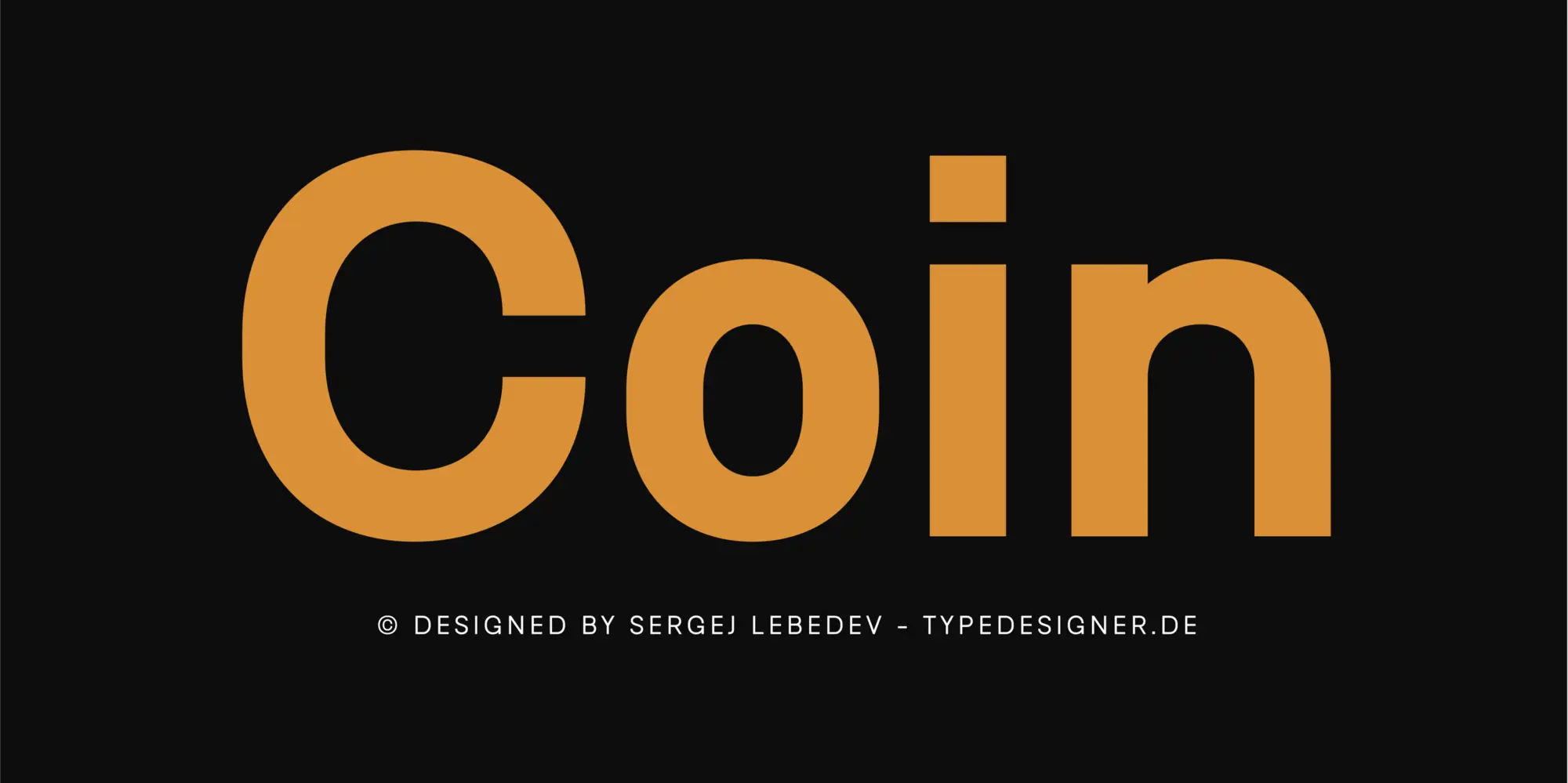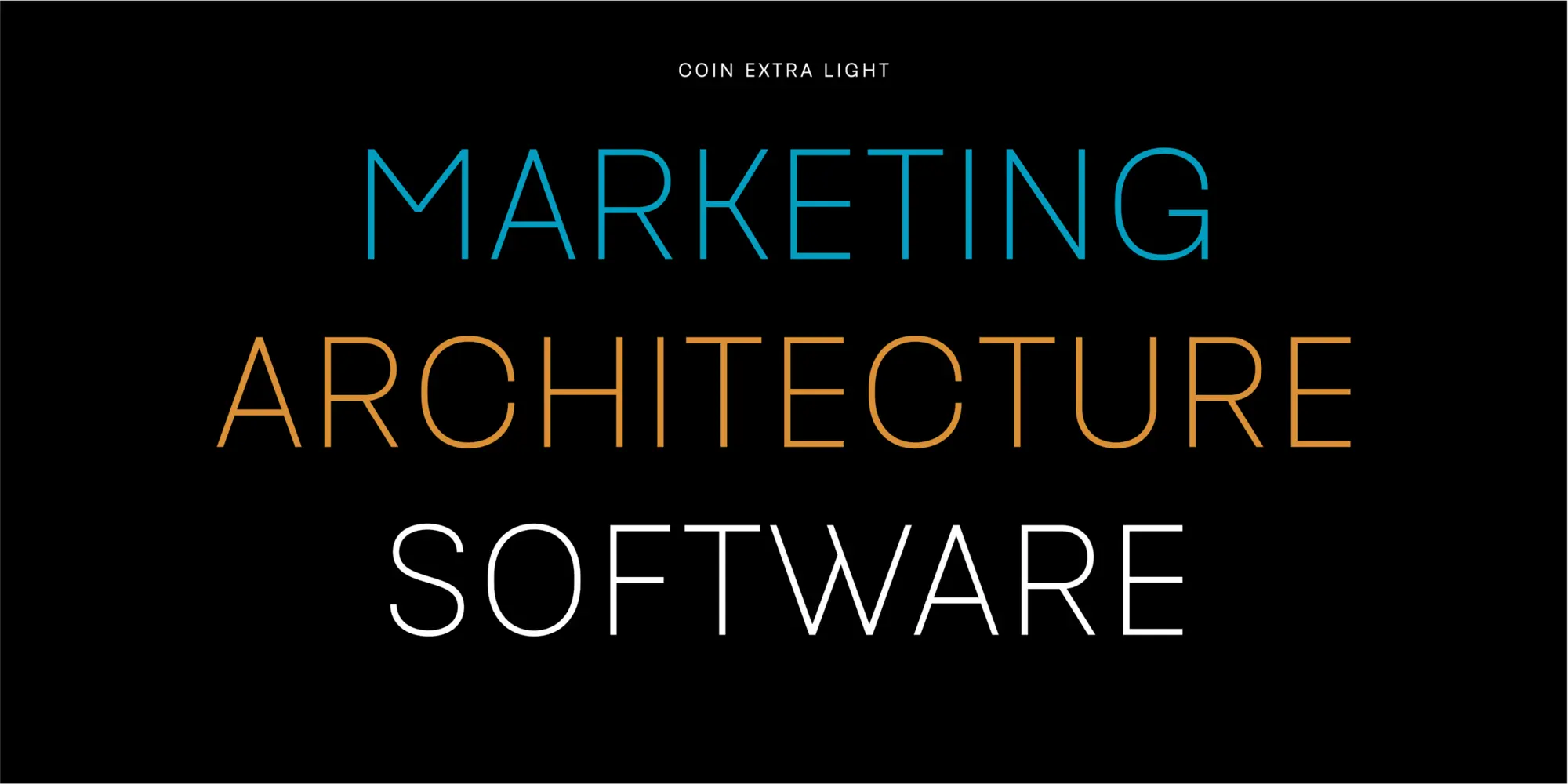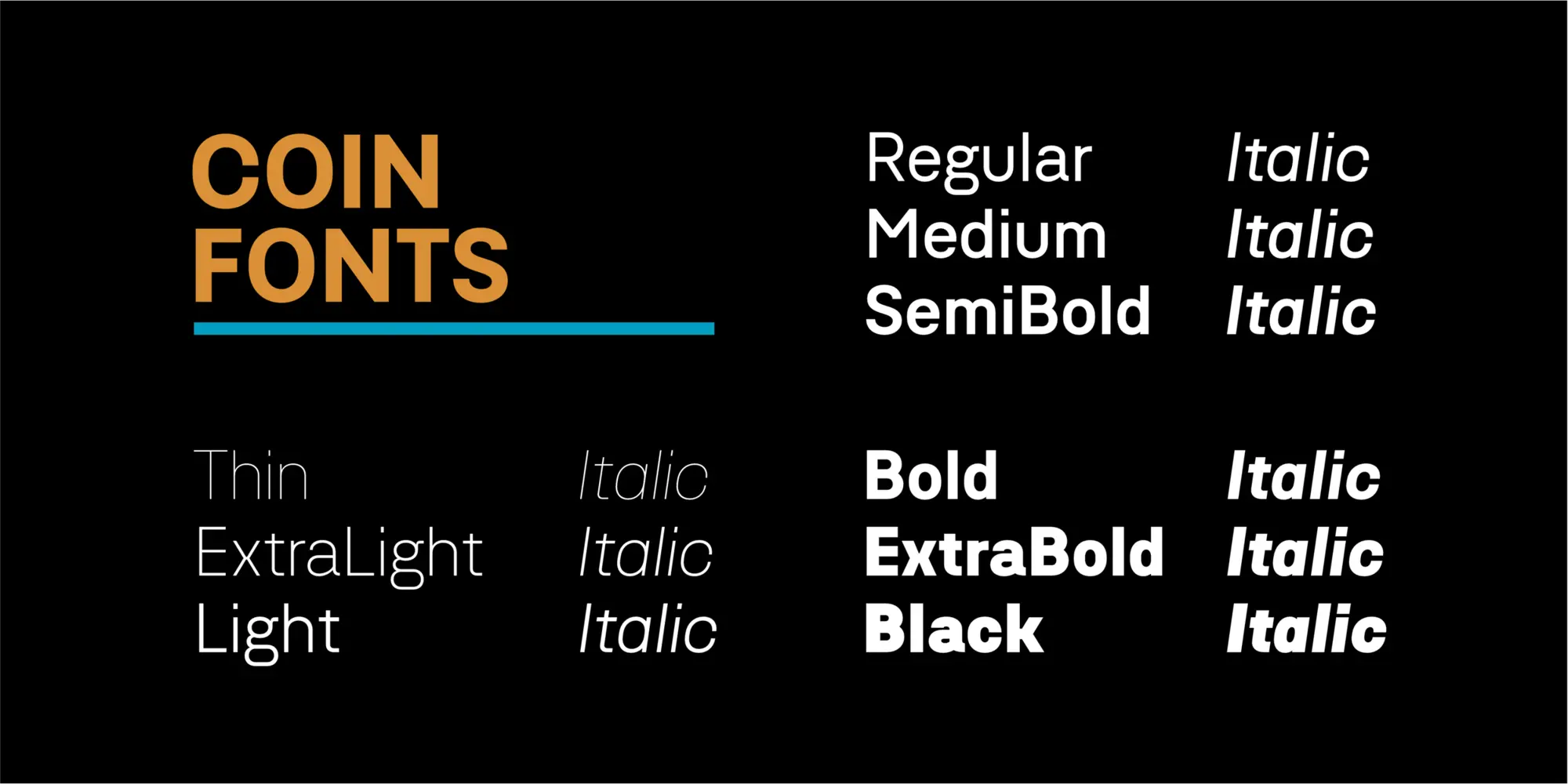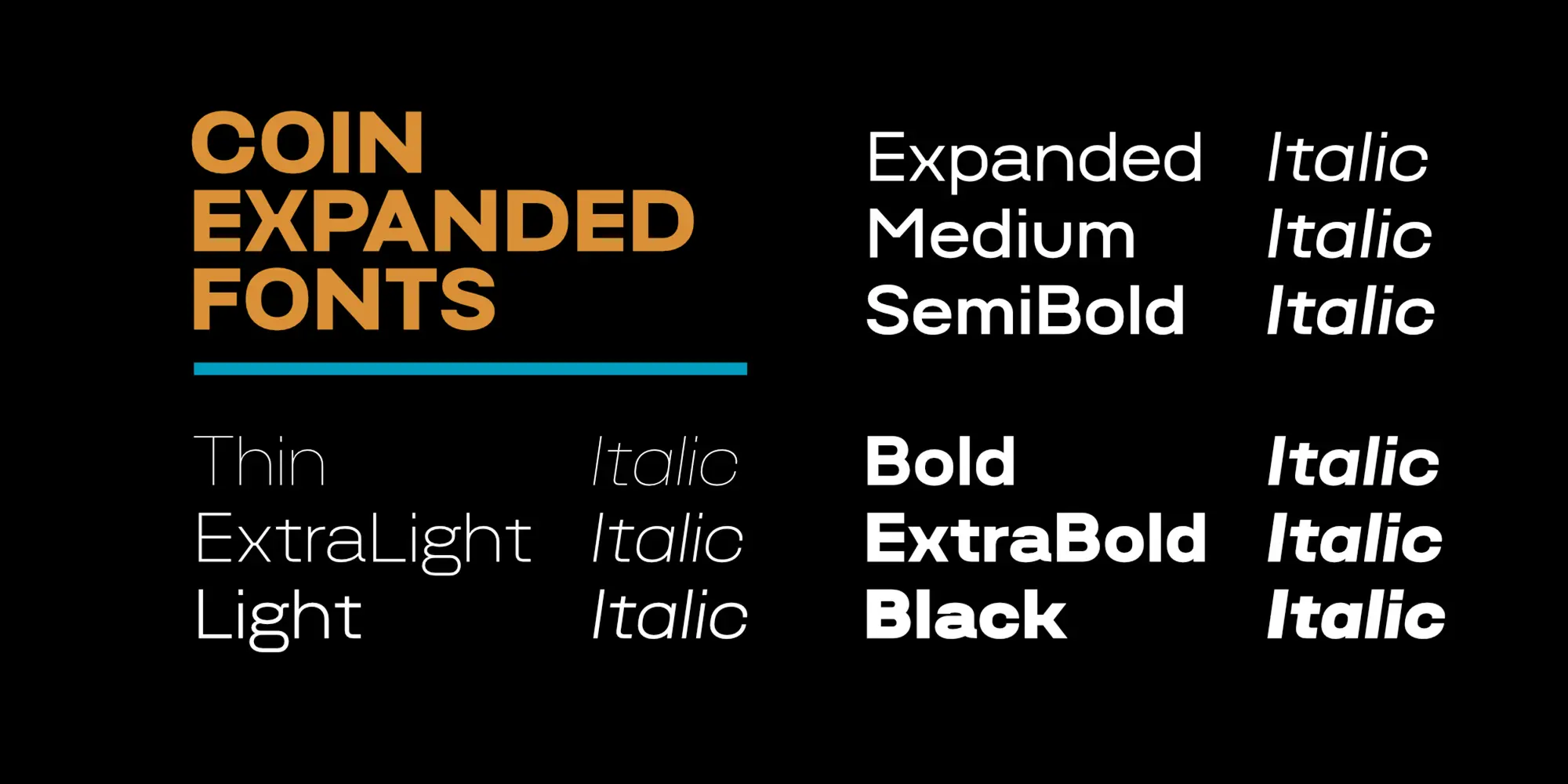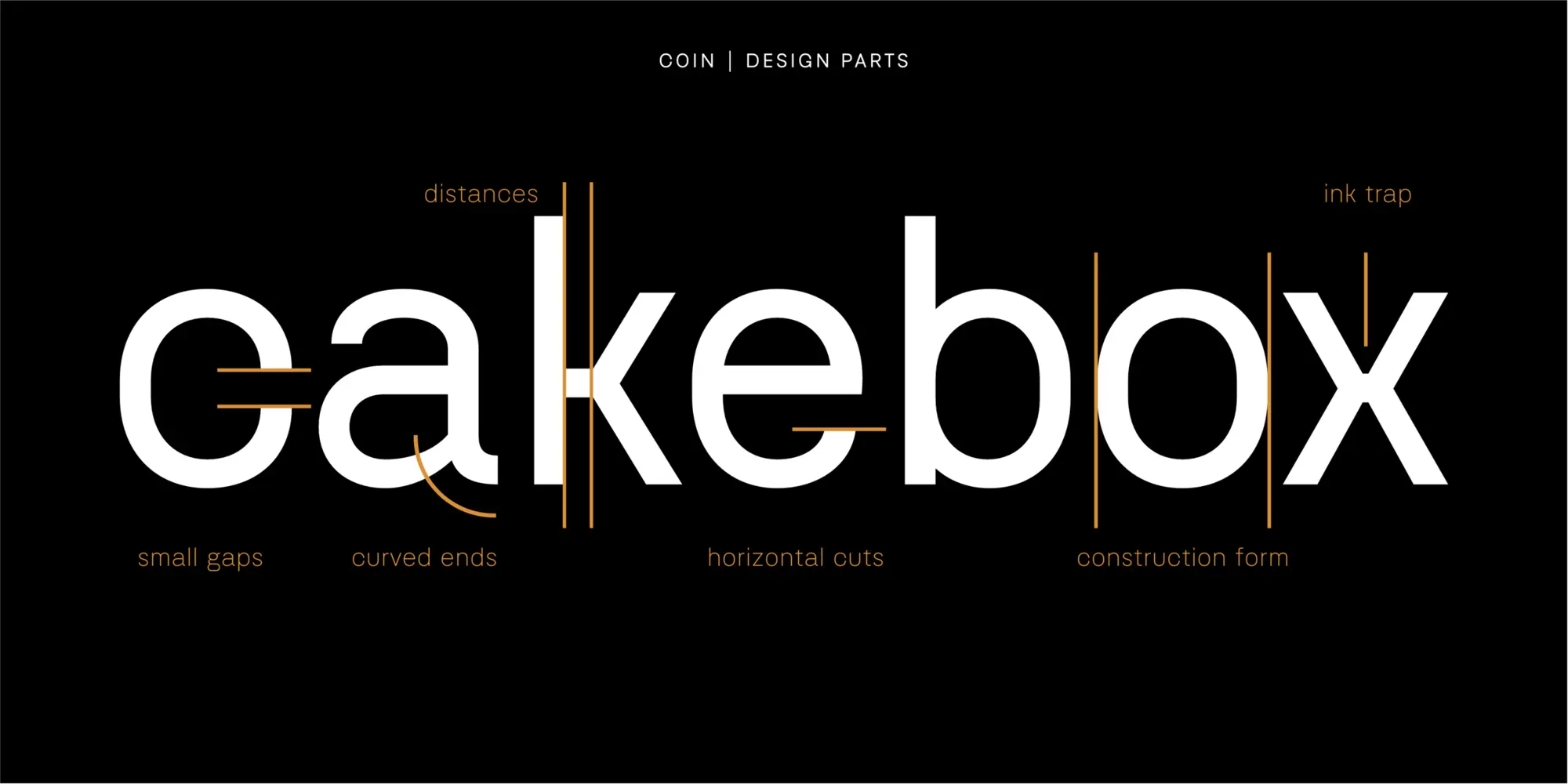
Die Schriftfamilie Coin von Sergej Lebedev umfasst 36 Einzelschriften sowie 4 variable Fonts. Der Zeichensatz umfasst rund 650 Zeichen inklusive zahlreicher Währungssymbole, darunter auch das Bitcoin-Zeichen. Ergänzt wird die Familie durch vielfältige OpenType-Funktionen und alternative Glyphenformen.